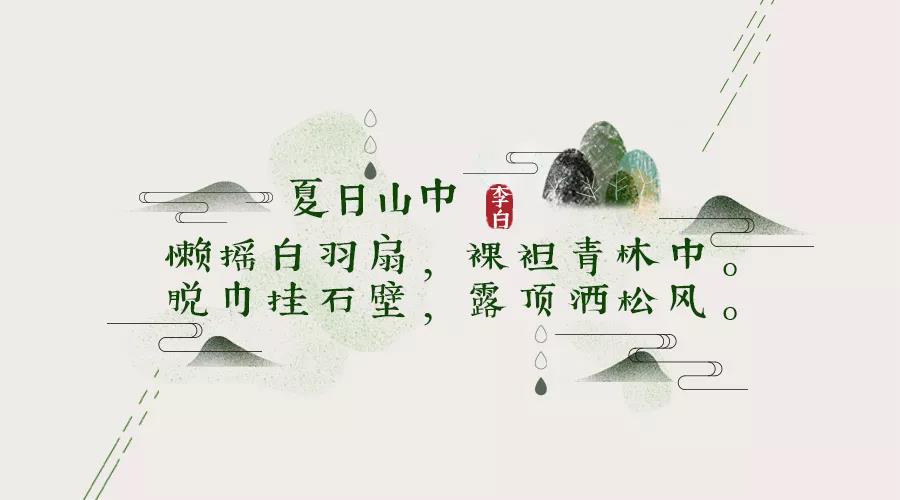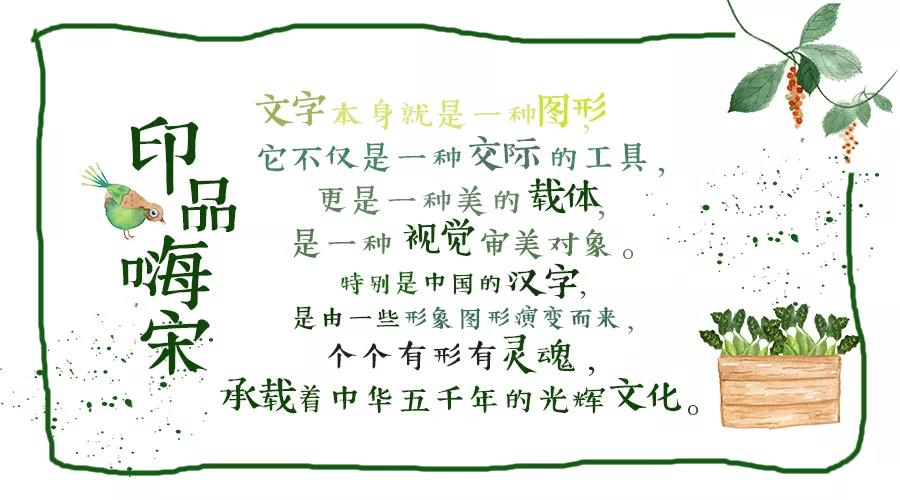
印品海宋體,是印品字庫出品的壹款根據宋體風格,壹改其嚴肅整齊的特點,通過對筆畫的個性化設計和字體大小的不同排版,使其更加可愛,讓用護感受不壹洋的個性宋體字。
字體的藝術性體現在其完美的外在形式與豐富的內涵之中,中國的印刷字體,以黑、宋、仿、楷爲代表。隨著移動互聯網時代的到來,娛樂、影音、媒介等數字載體,更多呈現的是超高清、2K、4K。
壹筆壹劃都透露著“個性”二字。
它就像壹位調皮可愛又腼腆的小男孩,
與衆不同卻存在感十足。
每壹次出場,
都讓人心情愉悅。
筆畫有粗細變化,橫細豎粗,末端有裝飾部分,點、撇、捺、鈎等筆畫有尖端,屬于襯線字體,偏向于宋體,但又和宋體不太壹樣。
重心並不保持在壹條直線上,給人壹種錯落有致的感覺。
“印品海宋”字體整體偏可愛風,字體大小的不壹致和重心高度的不統壹,更加表現了字體的個性與特點。
與衆不同是壹種個性標簽,
是壹種性格,